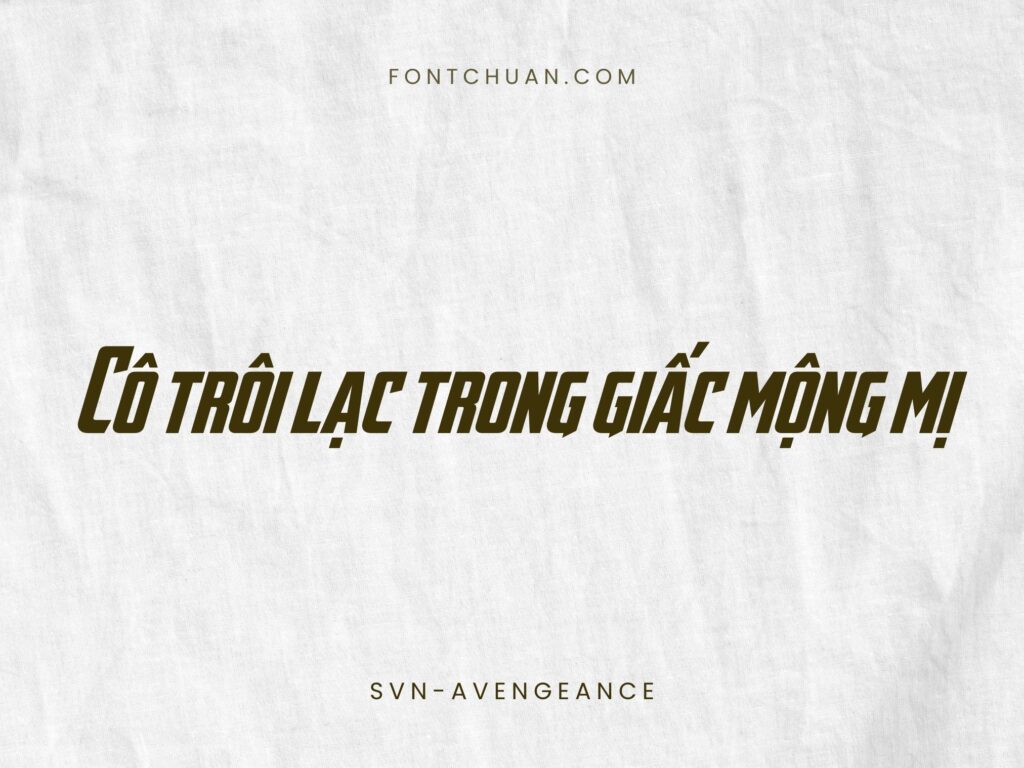
Font SVN Avengeance Việt Hóa
Font SVN Avengeance là phiên bản Việt hóa của kiểu chữ Avengeance, được thực hiện bởi Styleno.1 Fonts. Avengeance là một kiểu chữ sans-serif mạnh mẽ, nổi bật với các đường nét góc cạnh và hiện đại, tạo cảm giác năng động và quyết đoán. Font này từng được sử dụng trong loạt phim The Avengers của Marvel, mang đến sự liên tưởng đến các siêu anh hùng và hành động kịch tính.
SVN Avengeance lý tưởng cho các dự án thiết kế liên quan đến chủ đề phim ảnh, truyện tranh và các ấn phẩm truyền thông mang phong cách mạnh mẽ, dứt khoát. Các ngành nghề như quảng cáo và công nghệ có thể tận dụng font này để tạo sự thu hút thị giác. Ngoài ra, font cũng phù hợp cho các sự kiện như Halloween, Giáng sinh, Valentine và các dịp lễ hội đặc sắc.